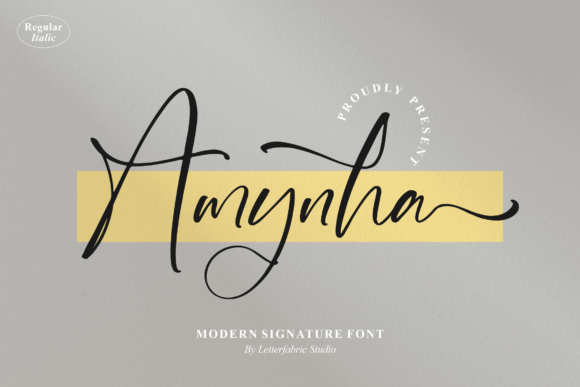
[Creativefabrica] Amynha Font (2022)
Amynha - современный фирменный шрифт подходит для любых проектов, таких как логотипы, брендинговые проекты, дизайн домашней одежды, упаковка продуктов, кружки, цитаты, плакаты, сумки, футболки, обложки книг, именные открытки, пригласительные билеты, поздравительные открытки, этикетки, фотографии, водяные знаки, специальные мероприятия и все другие ваши прекрасные проекты, которые нуждаются в красивом шрифтовом вкусе.